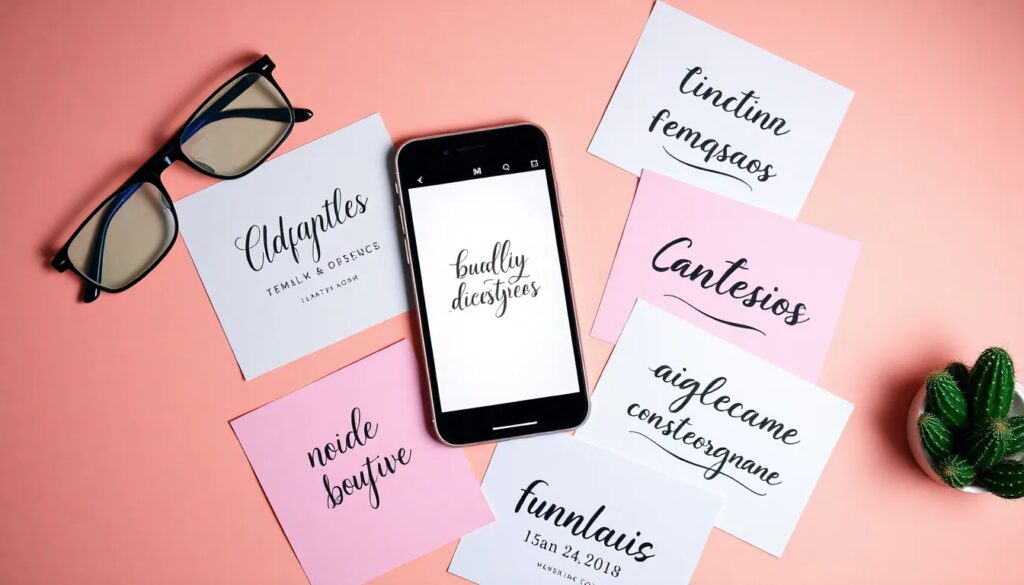
Instagram bio fonts: genera y copia estilos únicos
La personalización de tu perfil en Instagram se ha convertido en una necesidad para destacar en un mar de usuarios. Las fuentes de Instagram ofrecen una manera sencilla de hacer que tu biografía se vea única y atractiva. En este artículo, exploraremos cómo estas fuentes pueden transformar tu presencia digital y atraer más seguidores.
Conocer las instagram bio fonts y cómo aplicarlas correctamente puede marcar la diferencia entre un perfil ordinario y uno que realmente brille. A continuación, abordaremos los aspectos más relevantes sobre estas fuentes que te permitirán destacar en la plataforma.
¿Para qué sirven las fuentes de Instagram?
Las fuentes de Instagram tienen un propósito claro: mejorar la estética de tu perfil. Estas fuentes permiten que tu biografía, publicaciones y comentarios se vean más creativos y llamativos. A continuación, se presentan algunas de las principales funciones:
- Personalización de tu perfil para atraer a más seguidores.
- Destacar información importante, como tu profesión o pasiones.
- Crear una identidad visual única que refleje tu personalidad.
Además, las fuentes estilizadas pueden hacer que tus publicaciones se destaquen en el feed, aumentando la probabilidad de obtener más interacciones. Al usar fuentes originales, puedes comunicarte de manera más efectiva y divertida con tu audiencia.
¿Cómo funciona un generador de fuentes para Instagram?
Un generador de fuentes para Instagram es una herramienta en línea que convierte texto normal en diferentes estilos de fuente utilizando caracteres Unicode. Este proceso es bastante sencillo y se puede realizar en pocos pasos:
- Escribe el texto que deseas transformar.
- Selecciona el estilo de fuente que prefieras.
- Copia el texto estilizado para pegarlo en tu biografía o publicaciones.
Los generadores de fuentes permiten a los usuarios experimentar con diferentes estilos de texto, ofreciendo una manera divertida de personalizar su presencia en Instagram. Sin embargo, es importante recordar que no todos los estilos funcionan correctamente en todas las plataformas.
¿Cuáles son los beneficios de usar fuentes en Instagram?
Usar diferentes fuentes en tu perfil de Instagram puede ofrecer múltiples beneficios:
- Aumentar la visibilidad: Al usar fuentes inusuales, tu contenido puede destacar más que el de otros usuarios.
- Mostrar creatividad: Las fuentes estilizadas son una forma de expresar tu individualidad y creatividad.
- Mejorar la legibilidad: Algunas fuentes pueden hacer que el texto sea más fácil de leer y comprender.
Además, las fuentes de Instagram pueden ayudar a crear un sentido de coherencia visual en tu perfil, lo que es crucial para la construcción de una marca personal o profesional. Al seleccionar fuentes que resalten tu estilo personal, puedes construir una conexión más fuerte con tus seguidores.
¿Cómo cambiar la fuente en mi biografía de Instagram?
Cambiar la fuente en tu biografía de Instagram es un proceso rápido y sencillo. Aquí te explicamos cómo hacerlo:
- Accede a tu perfil de Instagram y toca "Editar perfil".
- Usa un generador de fuentes para crear el texto que deseas incluir.
- Copia el texto estilizado y pégalo en el campo de tu biografía.
- Guarda los cambios y revisa tu perfil.
Recuerda que es recomendable mantener la biografía breve y relevante, incluso al utilizar fuentes estilizadas. Esto ayudará a que los visitantes comprendan rápidamente quién eres y qué ofreces.
¿Qué fuentes funcionan en mi perfil de Instagram?
En Instagram, las fuentes que funcionan incluyen aquellas que se basan en el formato Unicode. Esto significa que cualquier estilo de texto que se pueda copiar y pegar será compatible. Algunas de las fuentes más populares son:
- Fuentes cursivas.
- Fuentes en negrita.
- Fuentes con símbolos decorativos.
Sin embargo, es importante tener en cuenta que algunos caracteres pueden no ser compatibles con Instagram y podrían ser eliminados al publicar. Por ello, es recomendable hacer pruebas antes de fijar tu biografía o publicaciones con fuentes estilizadas.
¿Dónde encontrar un generador de fuentes gratis para Instagram?
Existen numerosos generadores de fuentes gratuitos en línea que te permiten crear y copiar estilos únicos. Algunos de los más populares incluyen:
Explora estas herramientas para descubrir diferentes opciones de fuentes que se adapten a tu estilo y personalidad. Con instagram bio fonts, puedes generar y copiar estilos únicos que resalten en tu perfil.
La elección de un buen generador de fuentes puede abrir un mundo de posibilidades creativas. Al experimentar con diferentes estilos, podrás encontrar aquellos que realmente resalten tu personalidad.
Preguntas frecuentes sobre fuentes para Instagram
Si tienes dudas sobre el uso de fuentes en Instagram, aquí respondemos algunas de las preguntas más frecuentes:
- ¿Qué son las fuentes de Instagram? Son estilos de texto que permiten personalizar la apariencia de tu biografía y publicaciones.
- ¿Cómo puedo usar un generador de fuentes para Instagram? Simplemente escribe tu texto en el generador, elige un estilo y copia el resultado para usarlo en tu perfil.
- ¿Por qué debería usar fuentes en mi biografía de Instagram? Para destacar visualmente, mostrar creatividad y mejorar la legibilidad.
- ¿Qué estilos de fuentes son populares en Instagram? Fuentes cursivas, negritas y decorativas son algunas de las más utilizadas.
- ¿Son las fuentes para Instagram compatibles con otras redes sociales? No necesariamente; algunas fuentes pueden no funcionar igual en plataformas diferentes.
En resumen, el uso de instagram bio fonts es una excelente estrategia para personalizar y destacar tu perfil. Experimenta con diferentes estilos y encuentra aquellos que mejor se adapten a tu identidad. Recuerda siempre revisar la compatibilidad de las fuentes en diferentes plataformas para maximizar su efectividad.